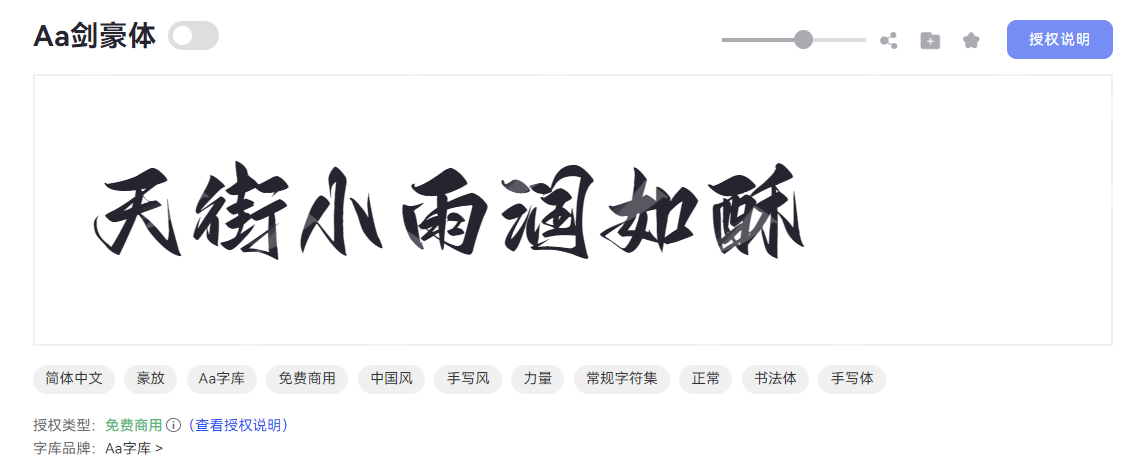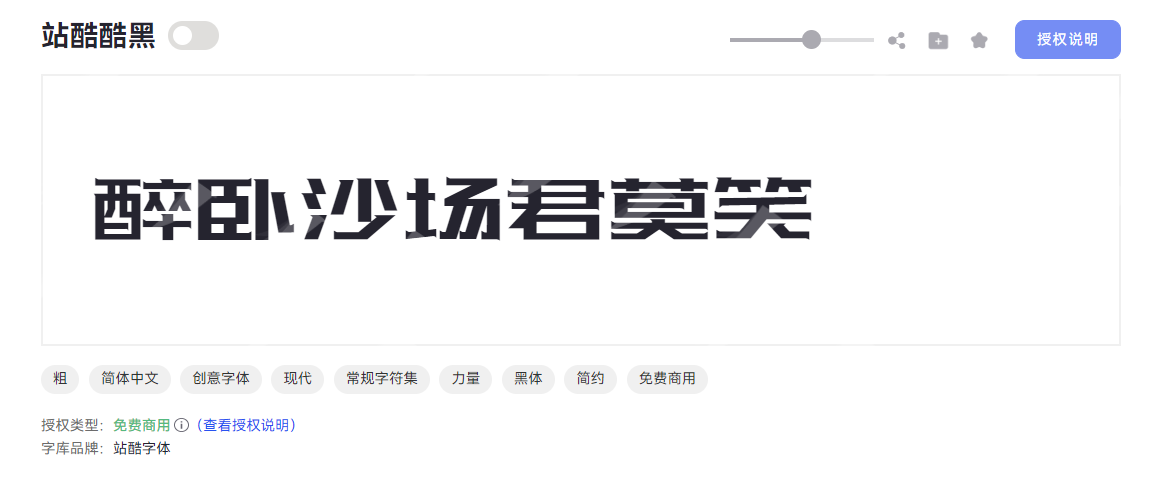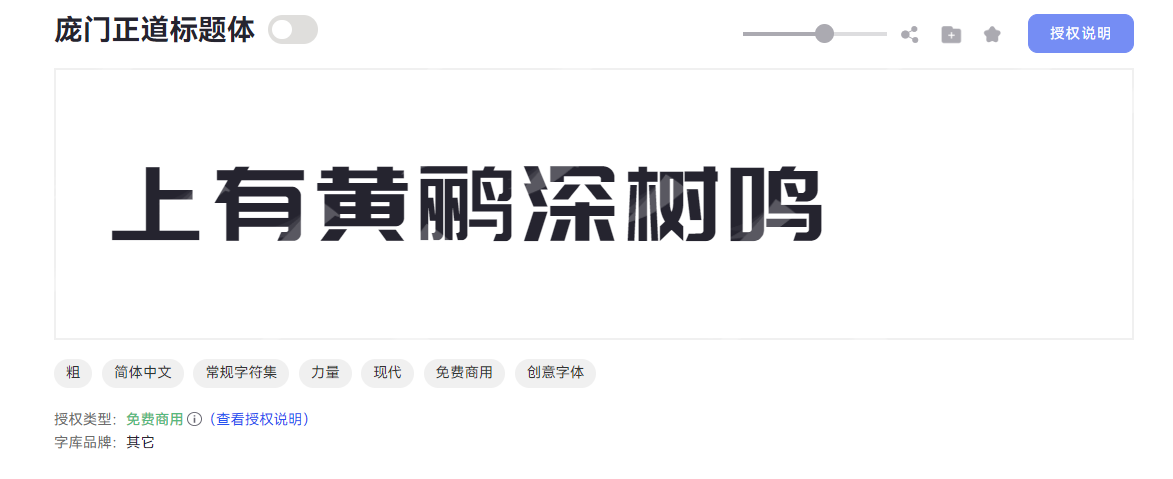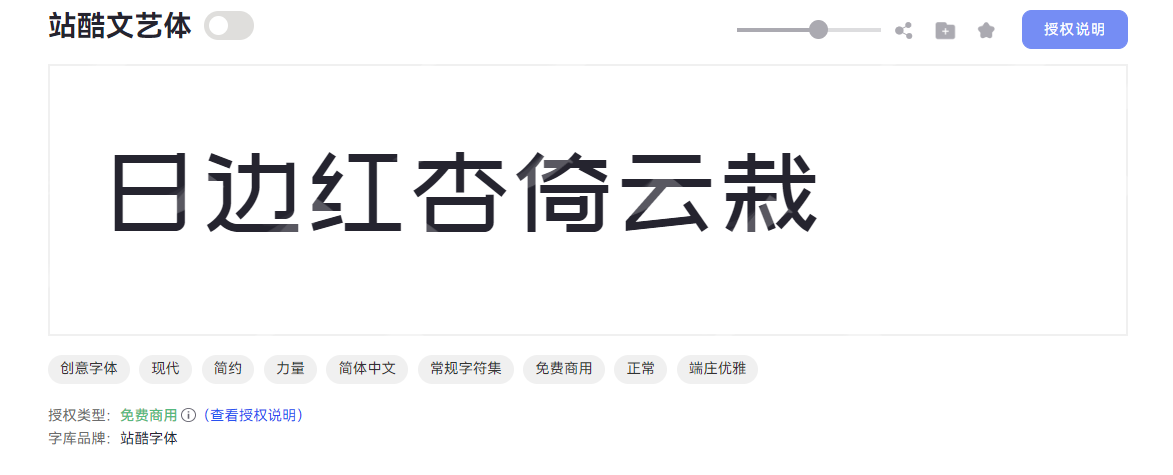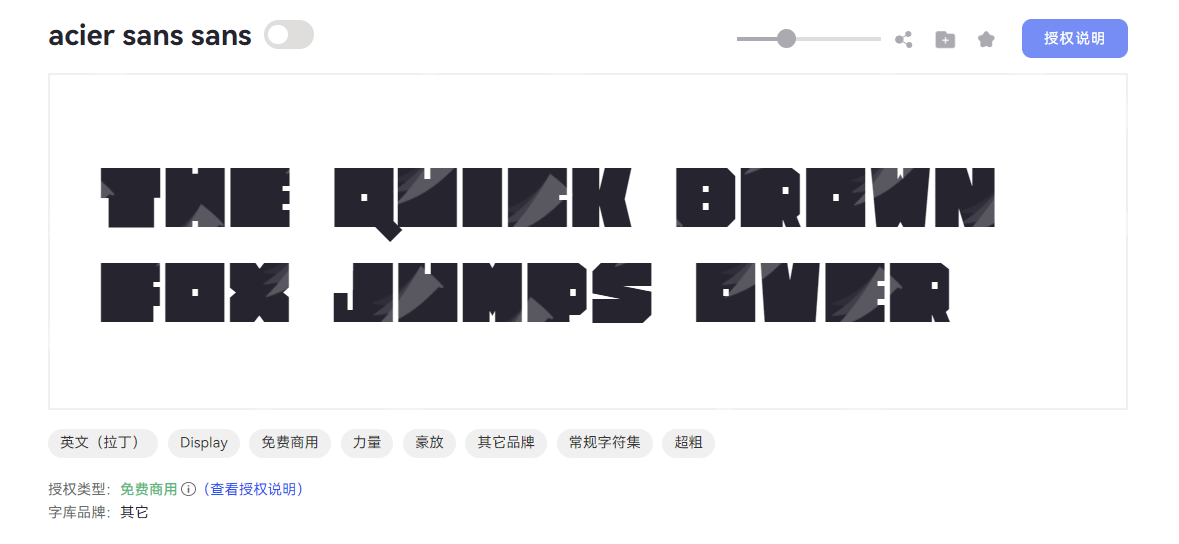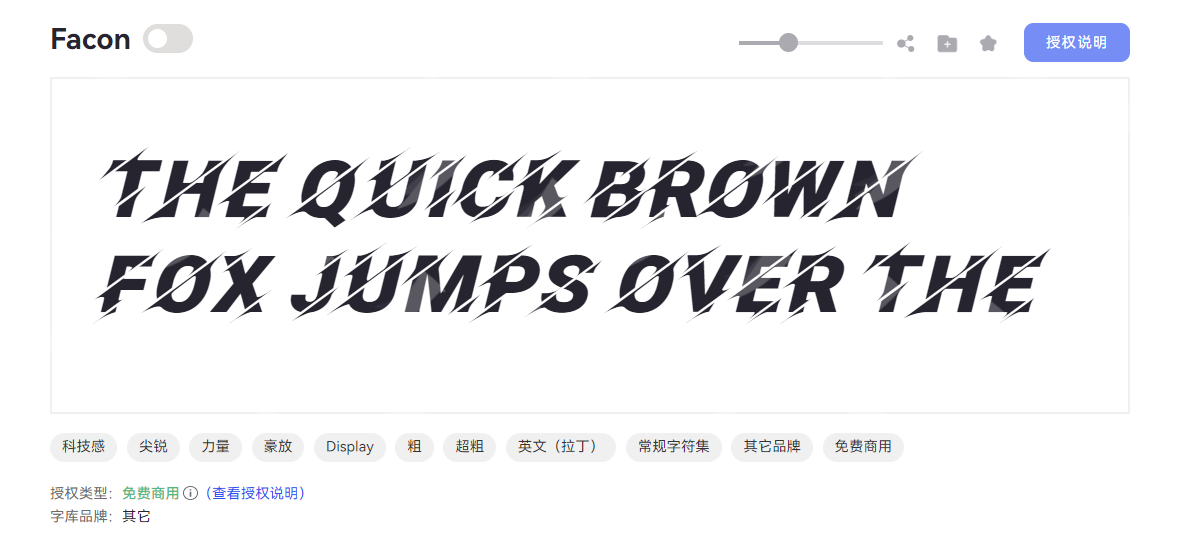
经常做设计的人都知道,标题字体是抓住观众视线的关键因素,尤其是活动宣传、促销推广类的海报设计,自带张力的力量感字体更是成为了很多设计师的首选。但网上搜索字体真的很容易踩坑,有些好看的字体不支持商用,有些免费字体又质量不高,影响作品的整体质感。所以,到底从哪可以下载免费商用的力量字体呢?选择一个合适的工具会少走很多弯路,字由就是一个不错的选择,它汇集了大量免费商用的字体资源,且版权标识清晰。本文就结合自身的使用体验,手把手教你如何下载免费商用的力量字体,并给你推荐几个很受欢迎的力量字体资源,帮你快速搞定海报标题用字。
二、免费商用的力量字体推荐
1.剑豪体
剑豪体一款中国风手写体,以“力量”与“豪放”为核心气质,将传统书法韵味与现代设计需求巧妙融合。字形修长劲挺,重心巧妙上移,宛如剑刃出鞘般利落;笔画粗重均匀,断连分明的处理既保留手写的随性,又透出剑势般的刚劲。剑豪体凭借其独特的中国风手写特质,广泛应用于武侠主题海报,传递豪迈洒脱的东方韵味,轻松用笔墨“剑影”打造兼具视觉冲击与文化底蕴的作品。
2.站酷酷黑
如果你追求现代极简风格,或者想要传递强劲视觉效果,站酷酷黑字体能为你的作品带来独特的魅力。这是一款创意黑体,以粗犷有力的笔画和方正宽博的字形著称,完美融合力量、现代、端庄、简约四大核心风格,是设计领域的实用之选。这款字体包含 3500 个常用简体汉字、52 个英文字母及 10 个阿拉伯数字,字符覆盖满足日常设计需求,兼具实用价值与艺术表现力。
3.庞门正道标题体
庞门正道标题体自上线之后,就凭借方正有力的字形、现代感的设计语言,快速抓住受众目光,经常被用于品牌主视觉标题、活动海报、电商 banner 等场景,有效传递出坚定且专业的品牌调性。他在字形结构上展现出鲜明个性:整体方正稳健,重心居中,中宫宽博,适合大字号标题场景下的清晰呈现;利落的直角线条构建骨架,搭配粗且均匀的笔画宽度,让每个字符都如建筑般棱角分明,既有秩序感又提供了舒适的阅读体验感。
4.站酷文艺体
有没有喜欢文艺质感的设计师,那你一定要好好收藏站酷文艺体。该字体以现代简约风格融合端庄优雅气质,成为设计领域备受青睐的文艺范字体。 字体字形修长,重心居中,中宫适中,整体结构均衡协调;笔画末端做圆润处理,搭配部分连笔设计,既保留端庄稳重的视觉印象,又透着清新淡雅的文艺气息。用站酷文艺体来做品牌宣传海报、文艺电影海报、书店活动推广海报,简直再合适不过了,轻松彰显简约而不简单的设计美学。
5.Acier Sans Sans
Acier Sans Sans 是一款以力量与豪放为灵魂的英文字体,凭借超粗字重与独特设计,成为标题视觉与焦点场景的亮眼之选。字体字形修长,在平衡的视觉框架下,超粗且均匀的笔画构建出强烈的存在感,让每一个字符都散发着硬朗的气场。如果你近期在做一些潮牌店铺、工业风视觉传达的设计项目,Acier Sans Sans 作为标题字体能够增强用户的视觉记忆点,瞬间抓住大家的目光。
6.Facon
Facon 是一款充满力量感且气质豪放的英文字体,完美融合科技感与视觉冲击力。字体采用修长字型设计,中宫宽博且重心居中,配合斜切笔型与方头笔画,形成极具辨识度的硬朗视觉语言。超粗字重与均匀的笔画分布强化了力量属性,而独特的笔画断开设计则为整体造型注入未来感。 作为免费商用字体,Facon 适用于游戏标题、科技产品包装等展示场景,传递硬核科技理念,助你打造前卫视觉符号!